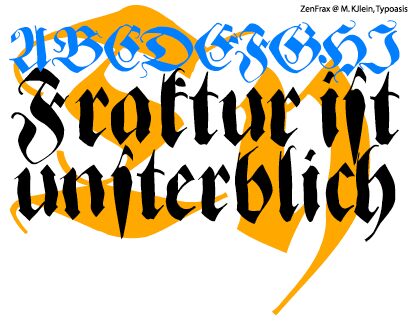
Zen Frax von Manfred Klein ist eine kostenlose mittelalterliche Gothic-Schrift mit einer messerscharfen, kalligrafischen Note. Sie besticht durch gebrochene Kurven, spitze Verbindungen und schwungvolle Blackletter-Elemente, was ihr einen unverwechselbaren, altmodischen Rhythmus verleiht, der eher feierlich als streng wirkt.
Die Schrift eignet sich hervorragend für Plakattitel, Buchcover, Fantasy-Branding, Eventgrafiken und Musik-Artwork – überall dort, wo ein historisches Flair gefragt ist, ohne dass das Design überladen wirkt. Da die Formen kompakte, dunkle Striche mit einigen langen, geschwungenen Gesten mischen, kommt ZenFrax besonders in kurzen Überschriften, Titelkarten und Monogramm-Initialen zur Geltung, wo diese Verzierungen den nötigen Raum haben, um zu wirken.